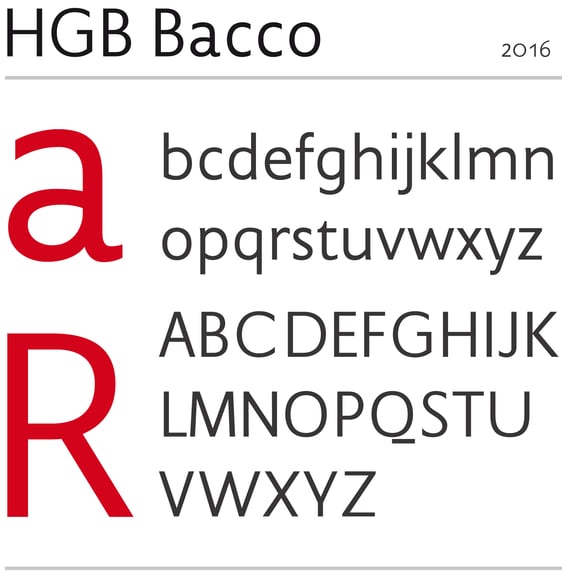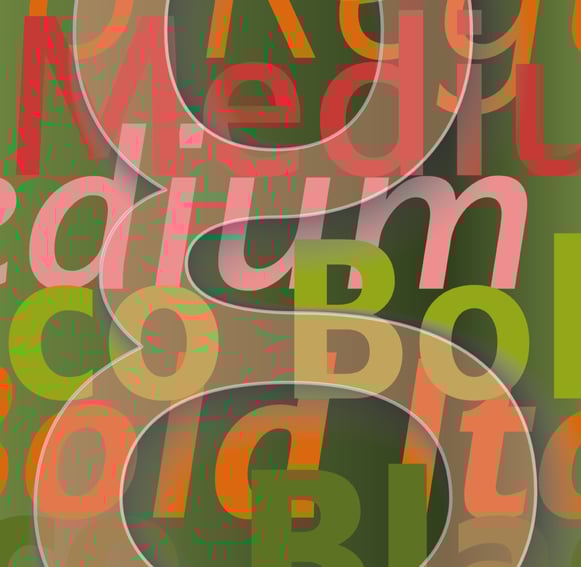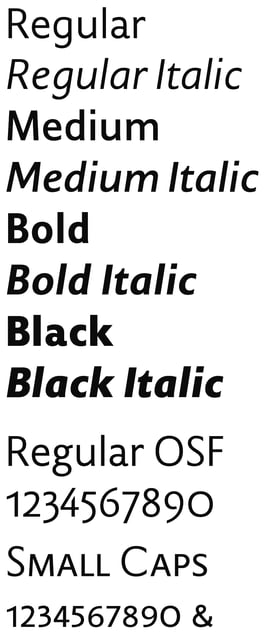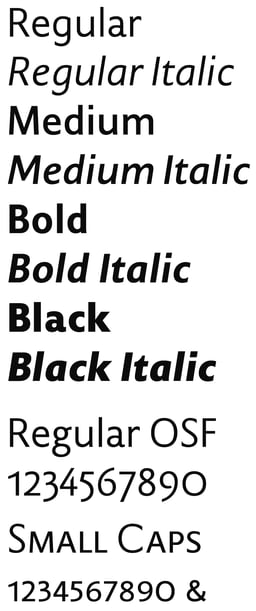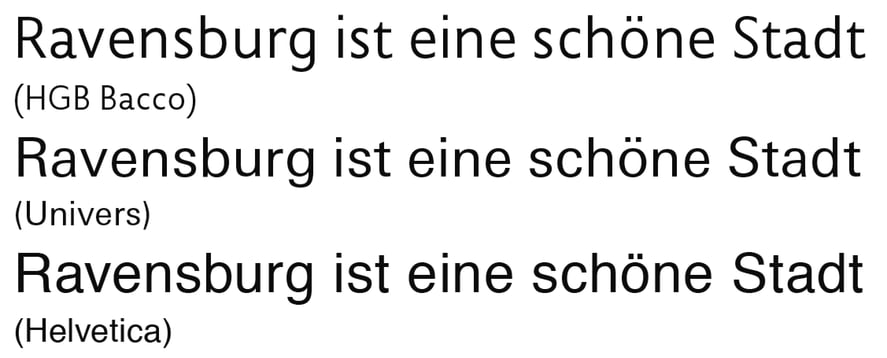
HGB Bacco
Seit 2005 gab es erste Versuche zu einer neutralen Grotesk mit humanistischem Charakter, aber erst nach Abschluss des Prolog-Projekts kam die »Bacco« auf einen guten Weg. Durch Einkreuzen von Elementen der Prolog Sans ergab sich ein befriedigendes Schriftbild. Die Ausstattung ist bewusst zurückhaltend, Alternativbuchstaben finden sich in den OSF-Schnitten (gß aduvy). Das Schriftbild sollte ähnlich wirken wie Helvetica und Univers, aber bei offeneren Formen und besserer Lesbarkeit bei längeren Texten. Die Bacco wurde ausgewählt als Satzschrift für das Buch »Planungsatlas Wien 1867 – 1918«. Seit November 2023 wird sie bei myFonts angeboten.